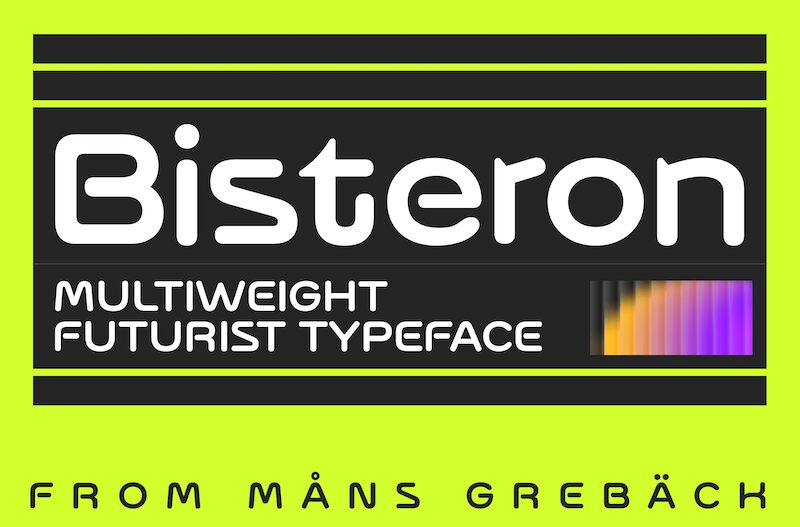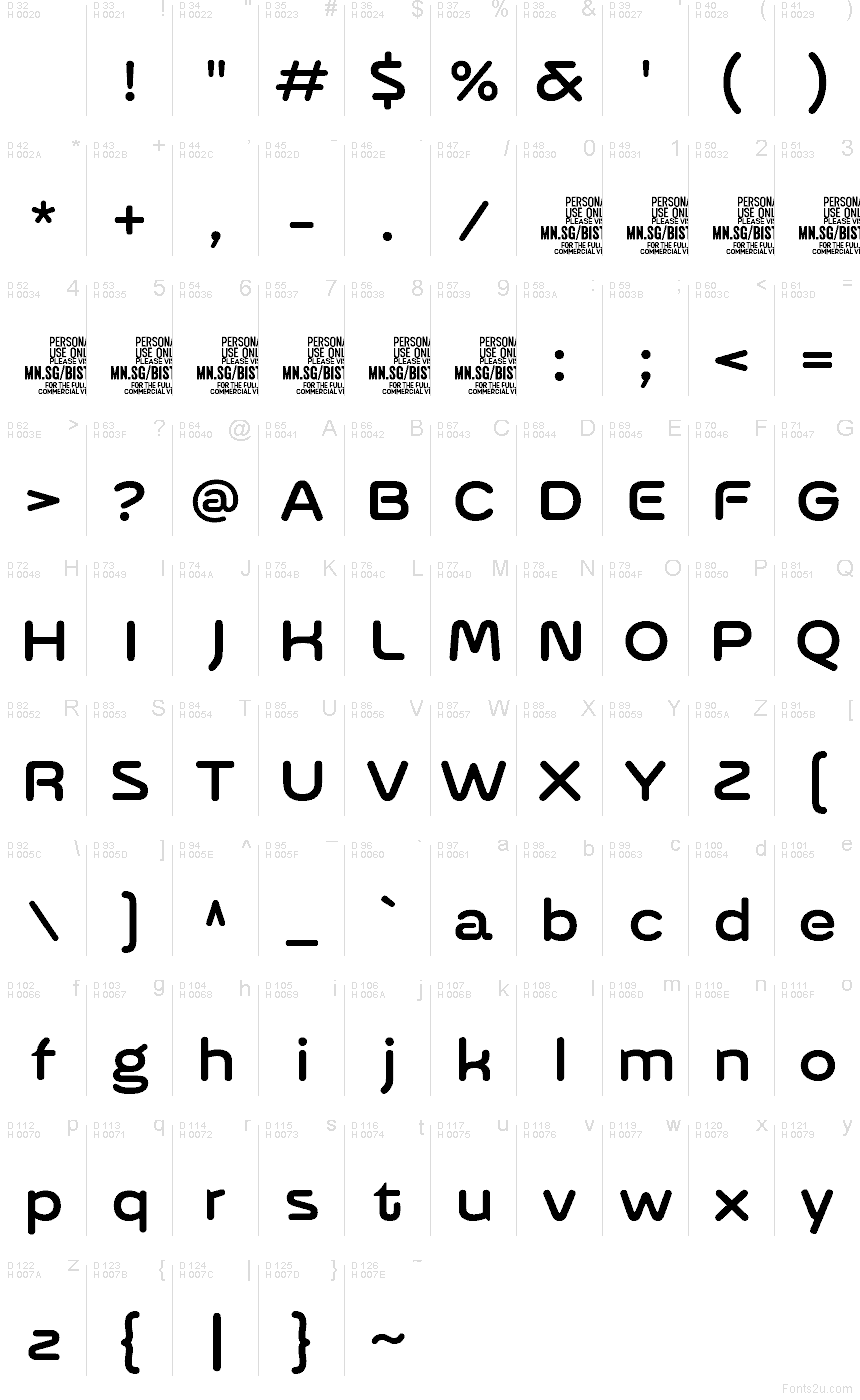
Bisteron PERSONAL USE Regular
Bisteron od Mans Greback AB je bezplatné futuristické písmo typu display, vytvorené na základe hladkej, zaoblenej siluety. Vďaka hranatým rohom a otvoreným rezom pôsobia písmená vzdušne a nie uzavreto. Táto opakujúca sa kombinácia jemných kriviek a zrezaných spojov dodáva dizajnu aerodynamický, syntetický rytmus, ktorý má bližšie ku grafike rozhraní než ku konvenčným geometrickým písmam.
Svoje uplatnenie nájde v technologickom brandingu, názvoch hier, úvodných obrazovkách aplikácií, sci-fi plagátoch a obaloch produktov, kde krátke slová vyžadujú elegantnú a technicky čistú prezentáciu. Keďže tvary zostávajú široké a zjednodušené, Bisteron dokáže skvele ukotviť logá aj nadpisy bez toho, aby stratil svoj výrazný elektronický charakter.